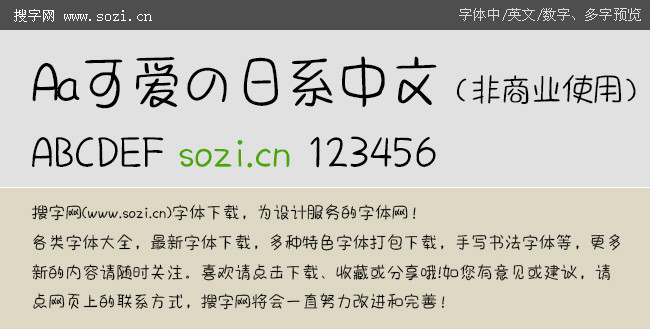
Aa可愛の日系中文
搜字網(wǎng)給大家提供一款A(yù)a可愛の日系中文(非商業(yè)使用)中文字體下載,該字體是一款可愛的藝術(shù)字體字體筆觸適中,字形圓潤(rùn)可愛,具有很好的視覺感。適合書裝設(shè)計(jì)、包裝設(shè)計(jì)、海報(bào)設(shè)計(jì)等應(yīng)用(此字體為個(gè)人非商用版,商用可以聯(lián)系QQ:1006760504)。